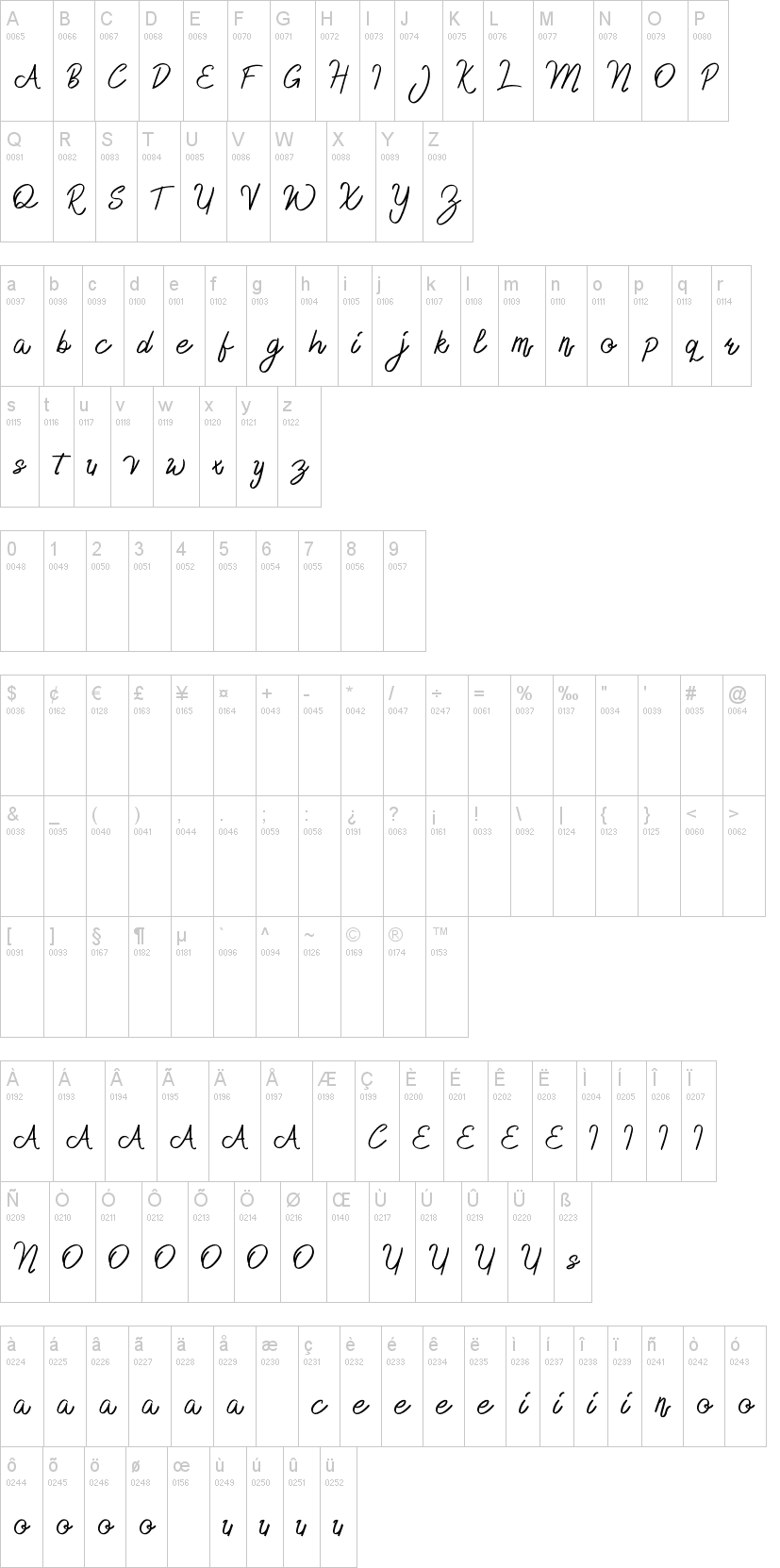
Delfoo是一款具有古典气息的英文字体,由西班牙设计师费尔南多·贝尔索创作,它拥有浓厚的经典感以及艺术感,更具有古典优雅的气质,是一款极具现代风格的字体。它的字体特征是细节处理精细,笔画粗细均衡,字距紧凑,空格开阔,且英文字母的结构设计比较精细,更具有艺术感,是一款英文字体中的精品。内容介绍
Delfoo是一款非常不错的手写艺术字体,具有很好的视觉感,适合于文化类的宣传设计、商业类品牌的广告和产品包装设计以及个性化文字排版等较多场景。